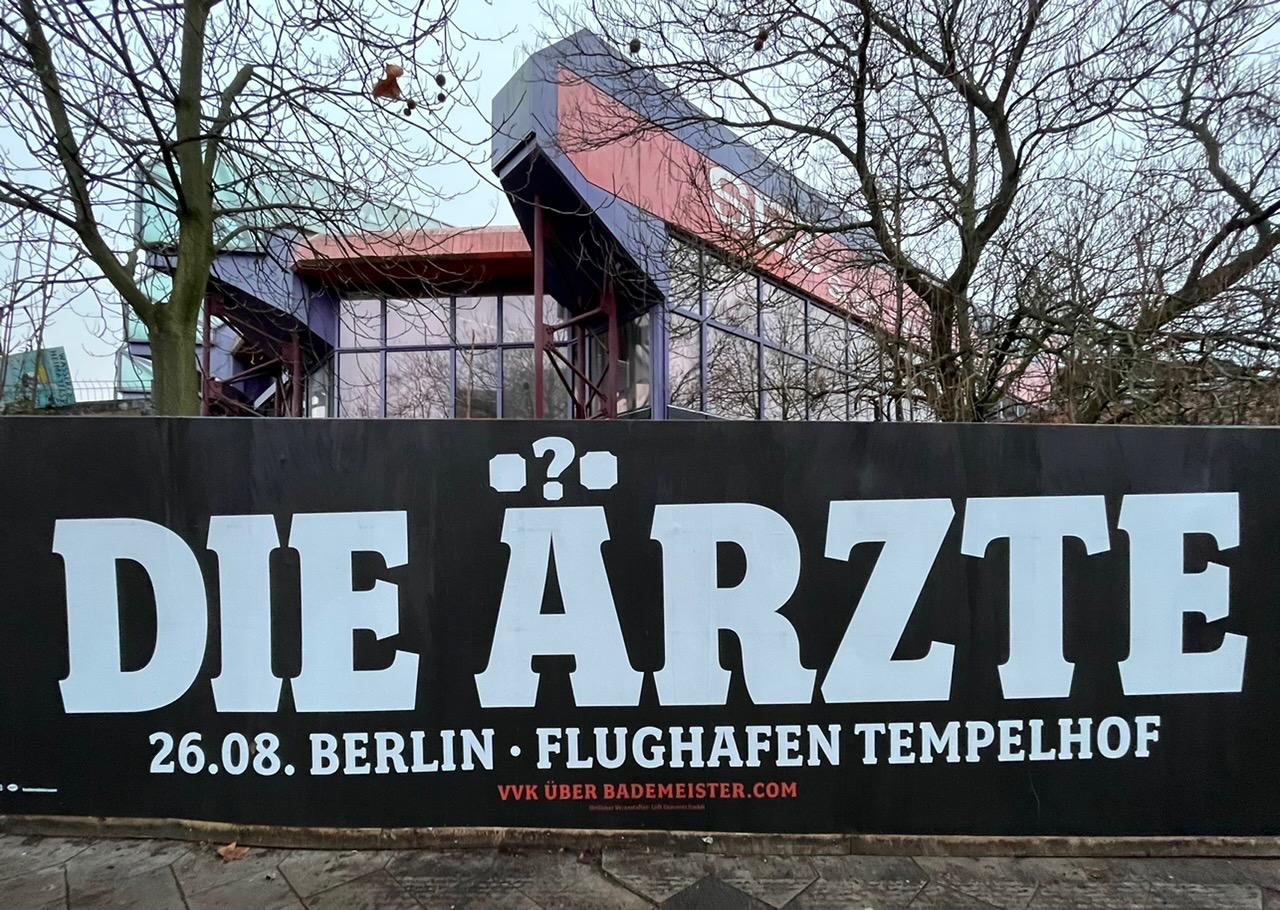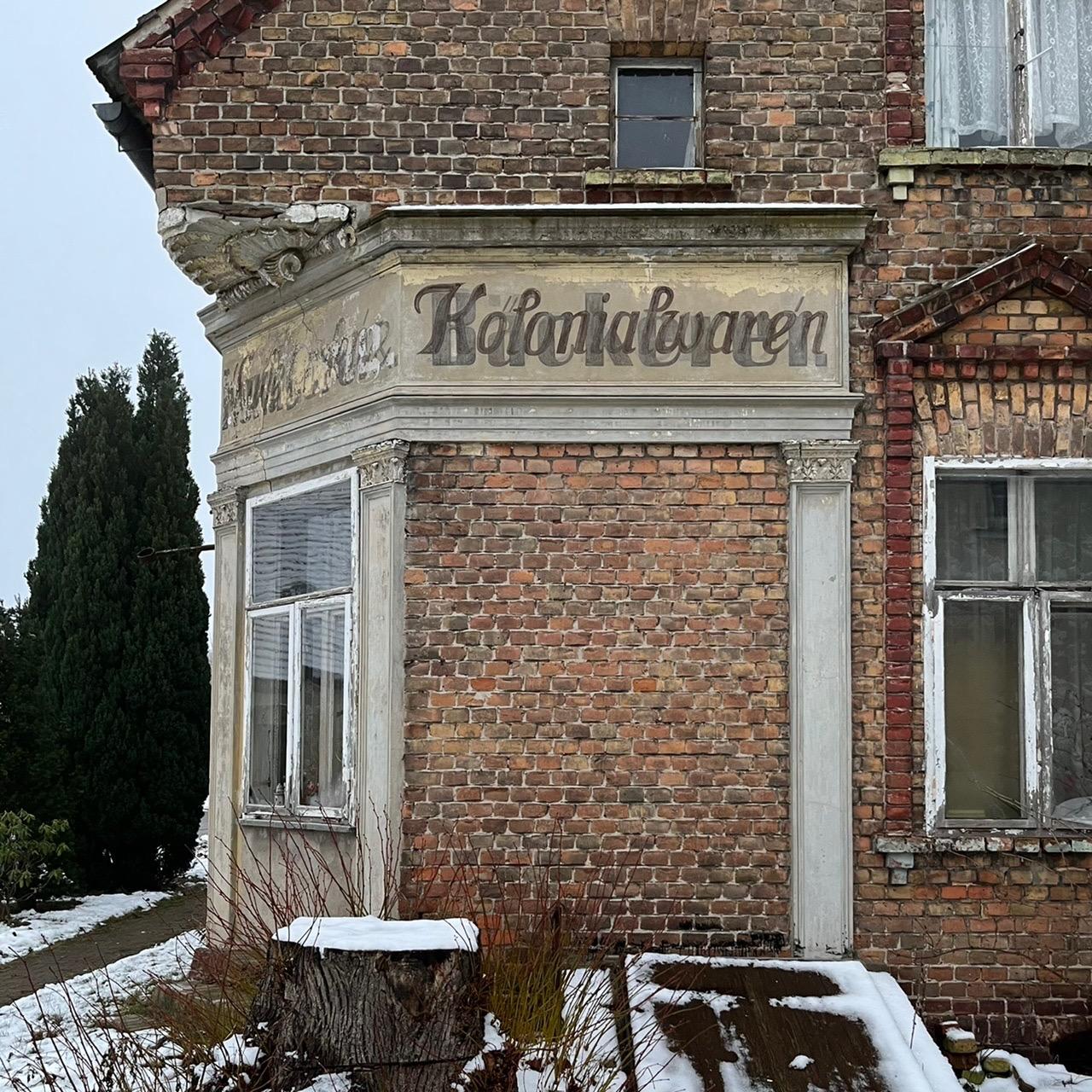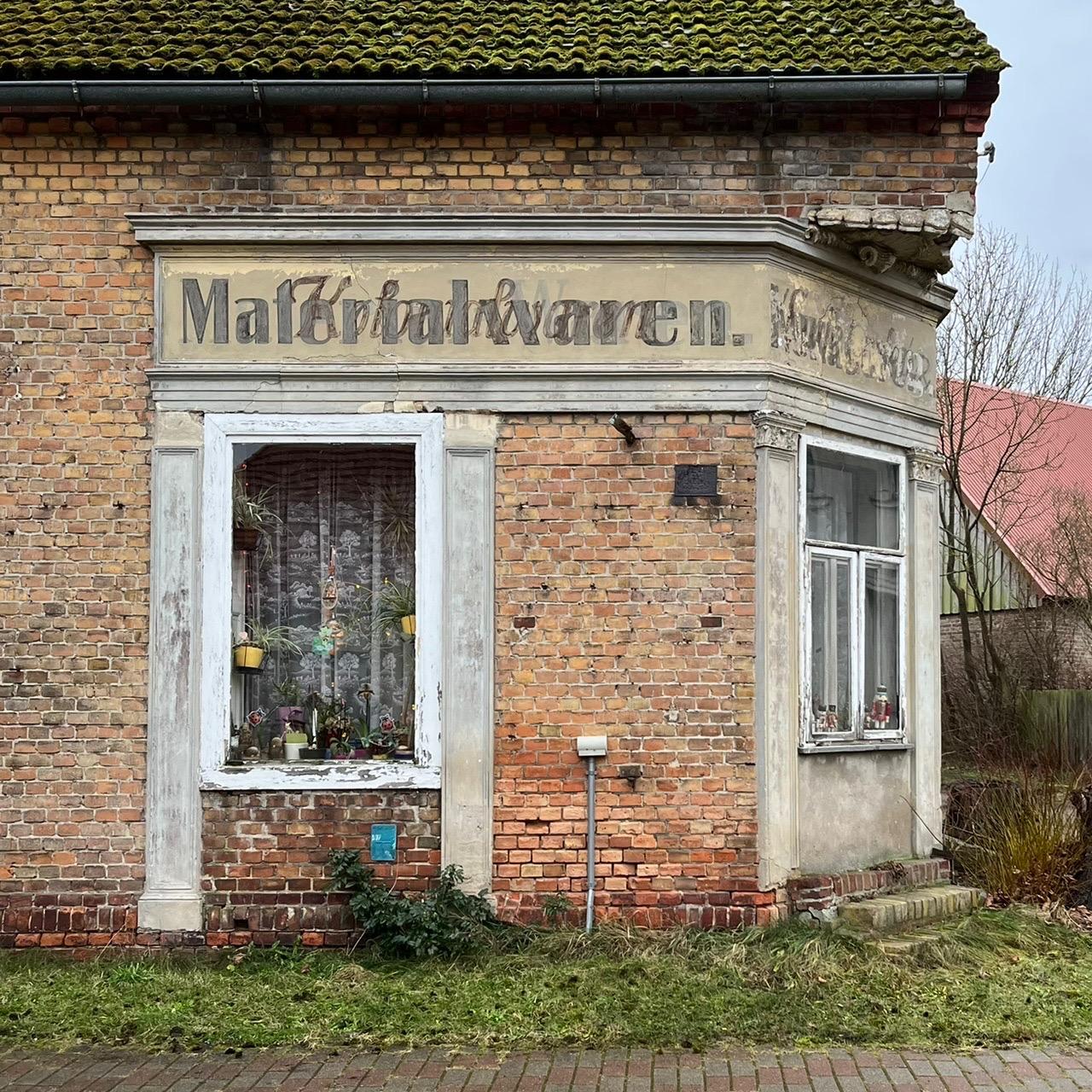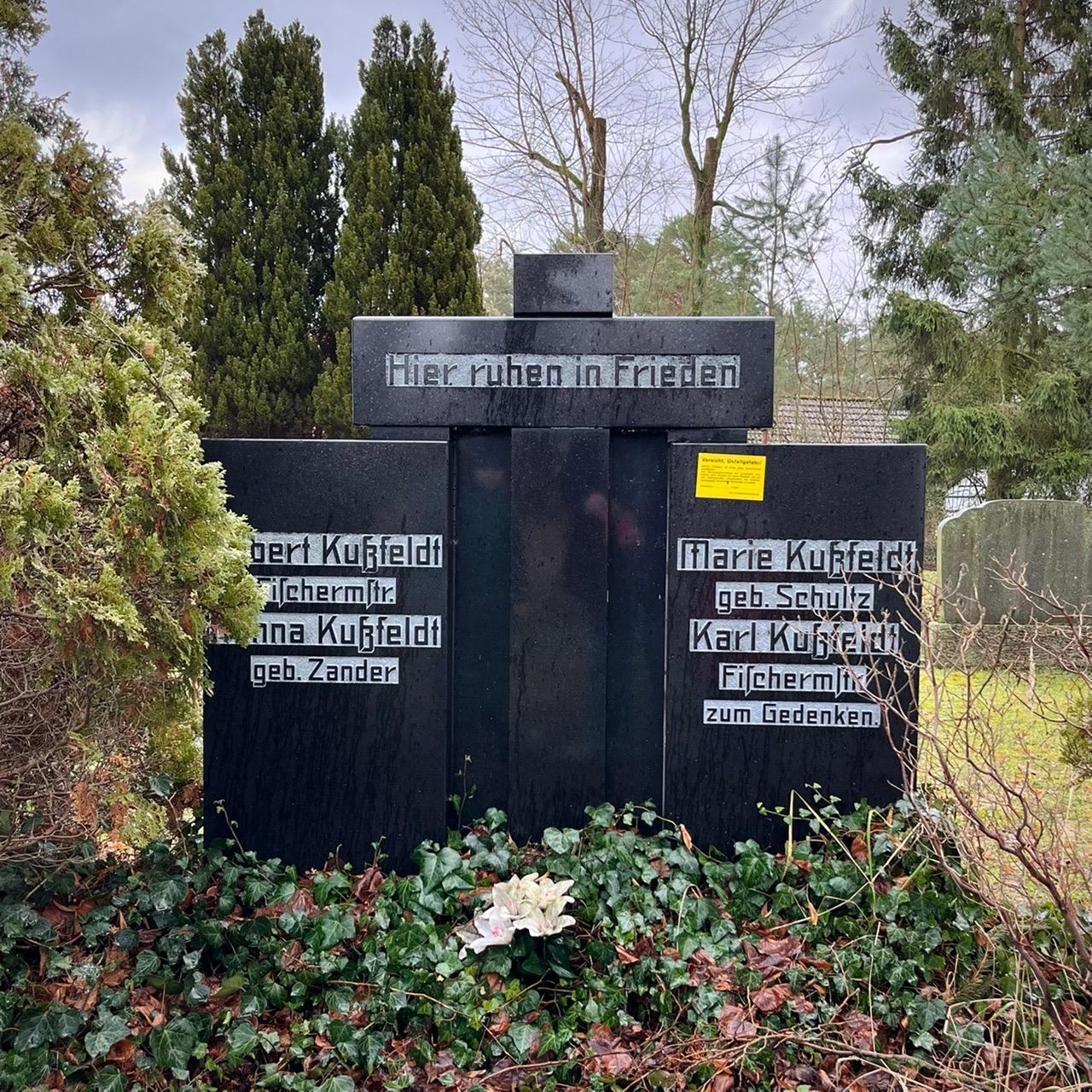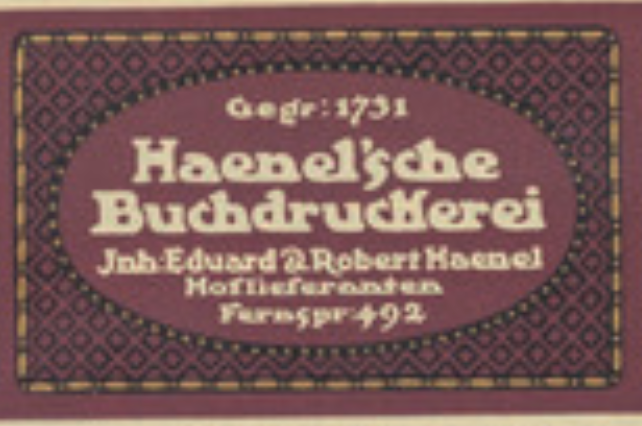
Ist bestimmt ein Wort aus einem vietnamesischen Dialekt, die stapeln doch knapp 1024 über ihren Buchstaben, hier ein Trema, ein Punkt und ein umgedrehter Ogonek ... ;-)
Wie sieht denn die weitere Umgebung dieses Buchstabens aus?
Das ist doch das (eigentlich) dreigepunktete »Ärzte«-Ä, das die Frage impliziert: »Wo ist Bela?«, oder?
Hoffentlich gibt es Menschen, die dieses ausdrucksvolle Haus genug lieben, um ihm eine schöne und lange Zukunft zu schenken!
Die Art Deco Schrift gefällt mir außerordentlich gut, die könnte i h gut als Druckschrift sehen.
Ich frage mich, wie so etwas zustande kommt. Man hat den Originalschriftzug übertüncht und eine neue Beschriftung angebracht. Dann ist aber nur die Tünche verblichen und ließ beide Beschriftungen stehen, ja?
Das muss aber mindestens zweimal passiert sein, denn unter den beiden oberen Schriftzügen (Materialwaren und Kolonialwaren) scheint noch ein weiterer (Waren) durch. Dessen „W“ beginnt direkt hinter dem zweiten l der kursiven Kolonialwaren. Vielleicht stand da aber auch mal „Material Waren“ und das wurde später in eine Zusammenschreibung korrigiert? Dann hätte man nur den jetzt sehr verblichenen Schriftzug „Waren“ abgewaschen oder übertüncht und dann neu drüber geschrieben. Hm. Erstaunlich ist auf alle Fälle, wie stark der kursive Schriftzug wieder durchgekommen ist. Spannend!
Au fein – das sieht hübsch aus! Und über den »Fernsprecher« wird sich der Kollege Pachulke sicherlich sehr freuen, wenn er hier mal wieder vorbeischneit. Danke fürs Zeigen. :-D